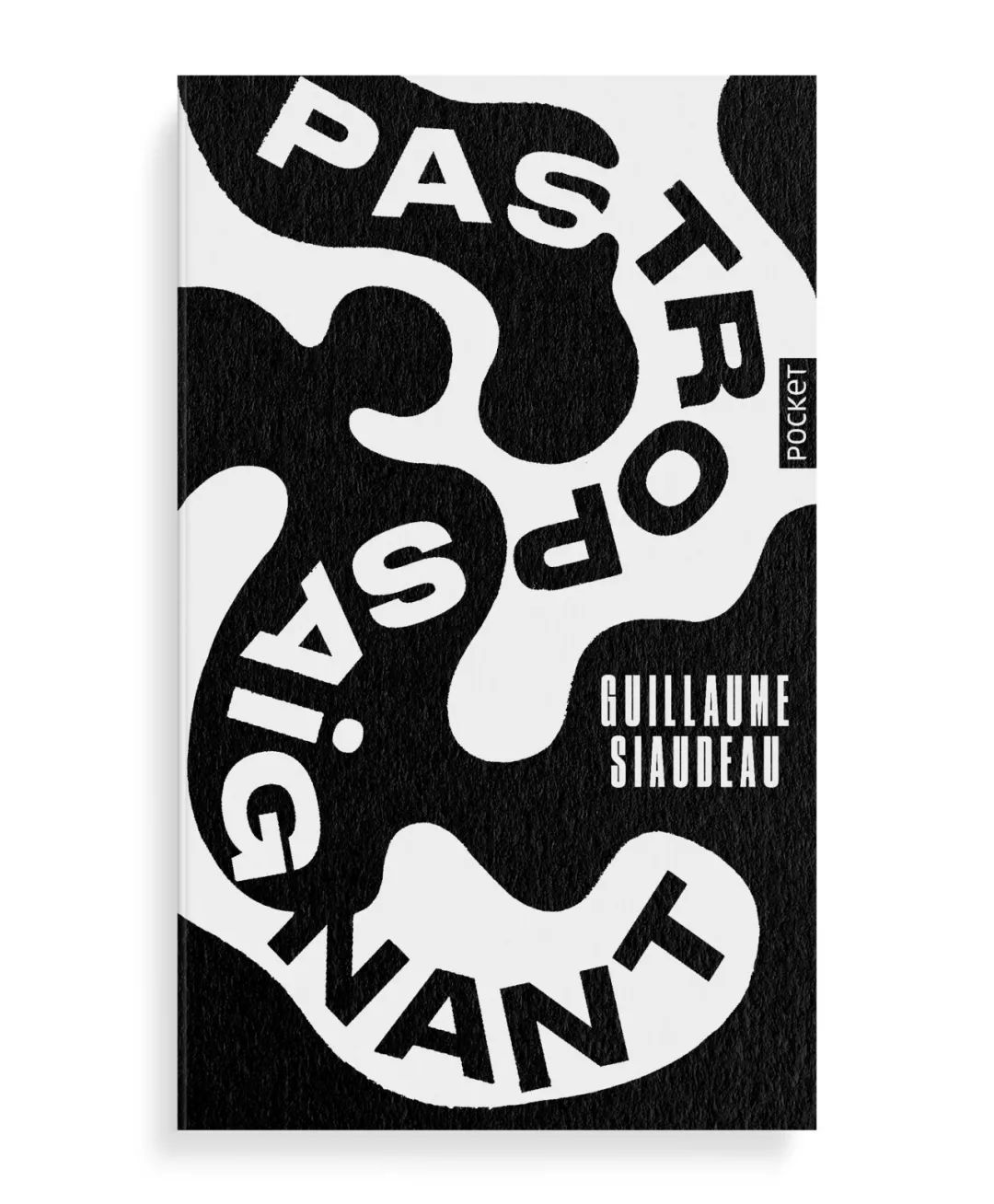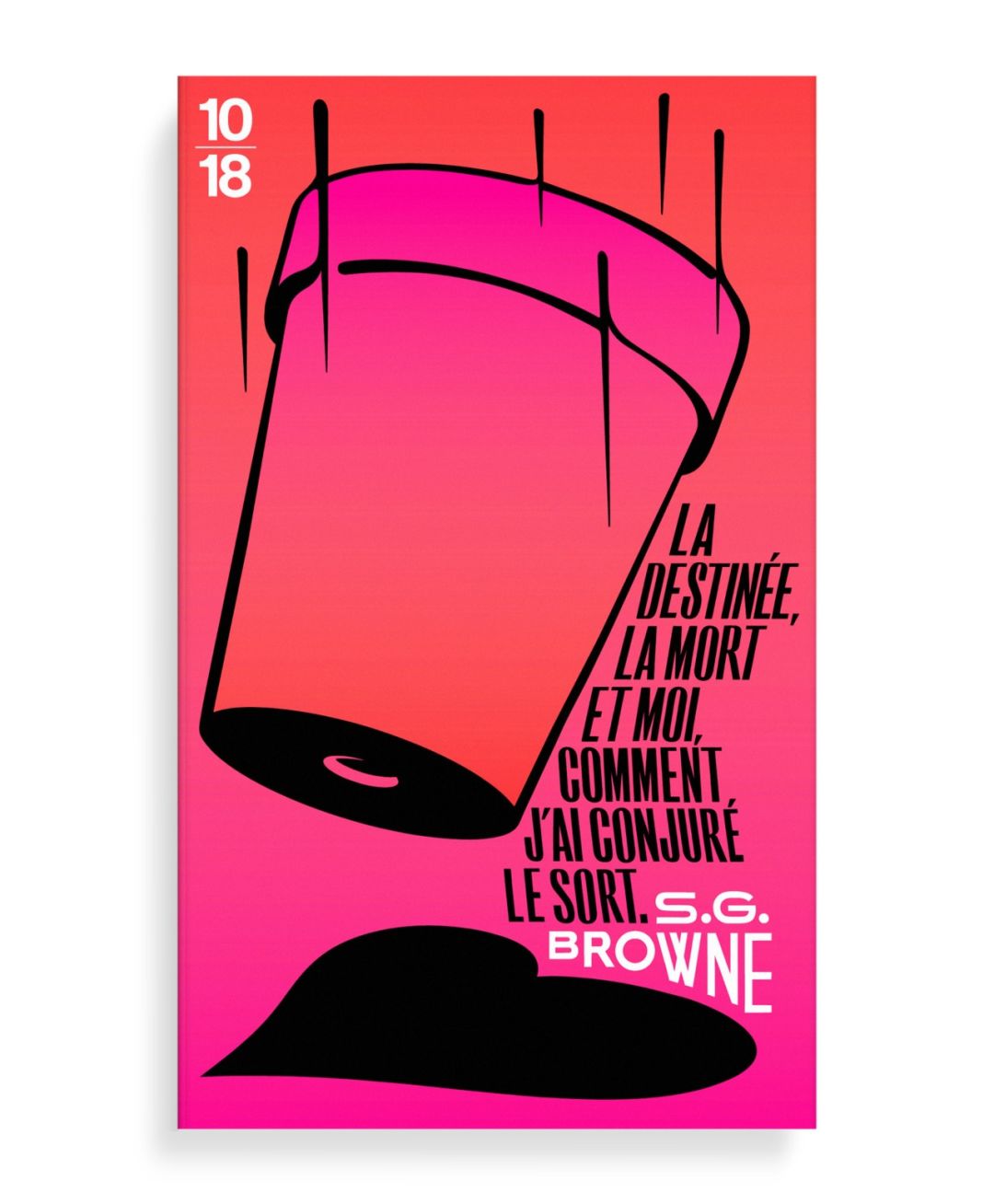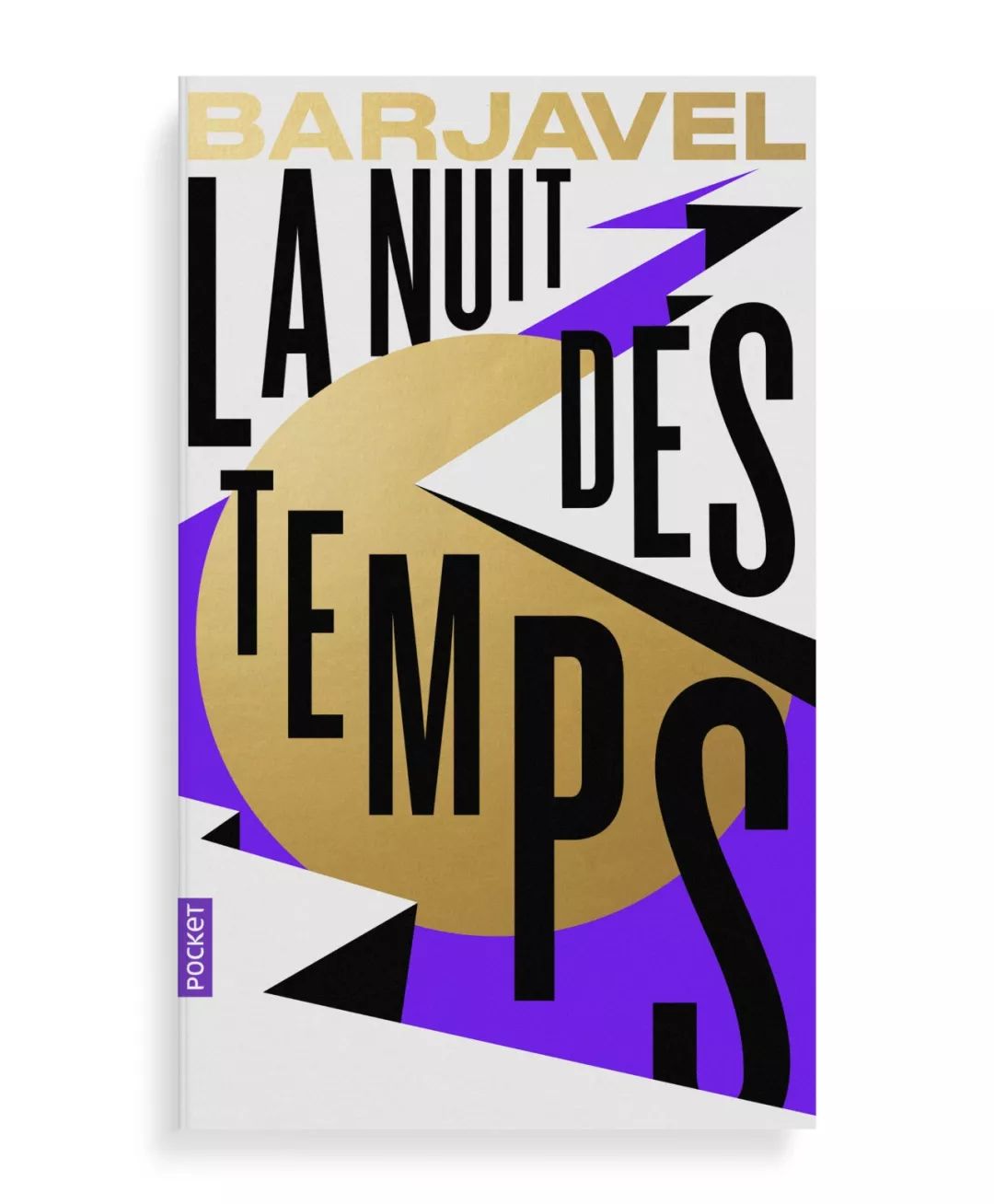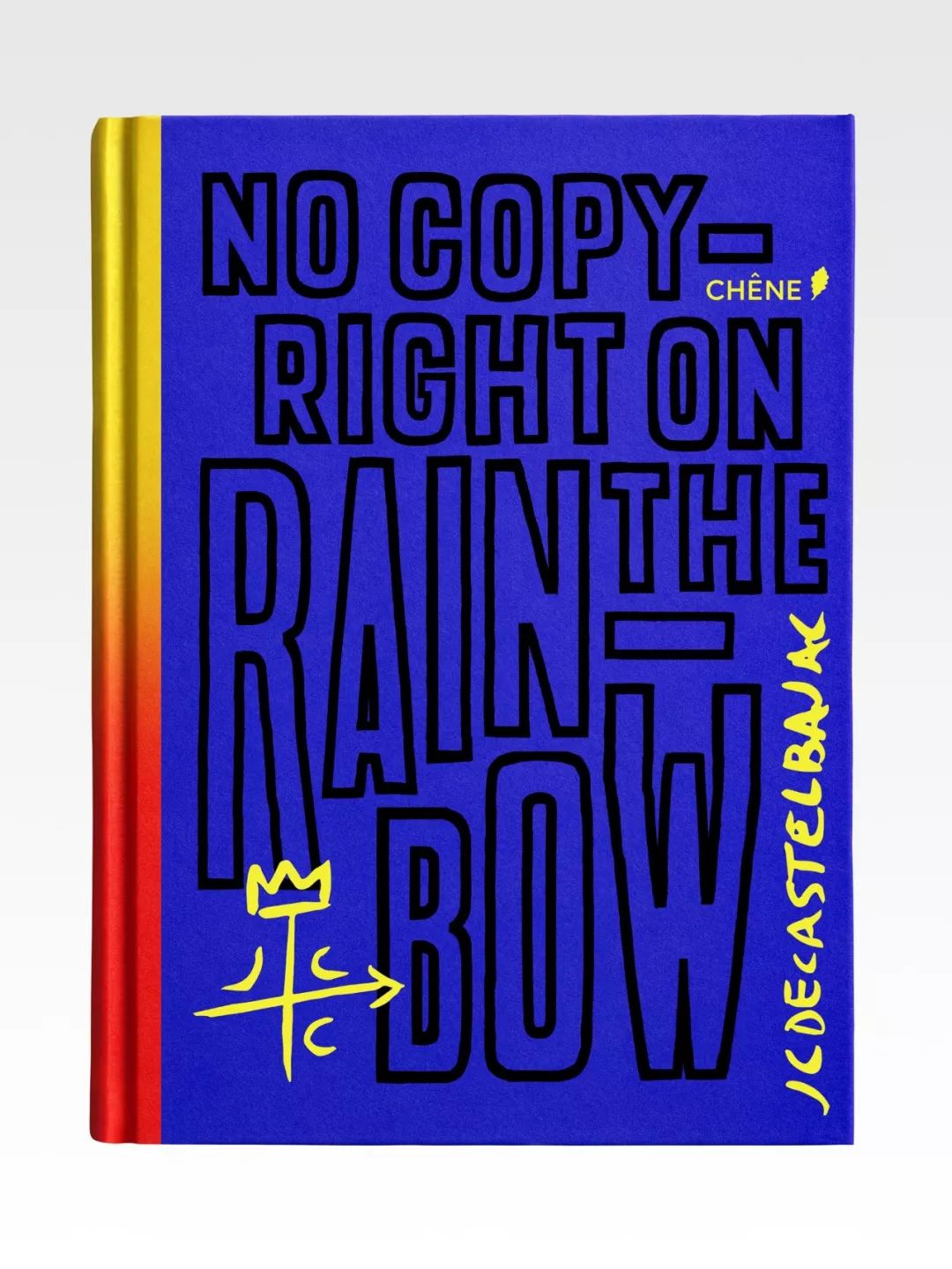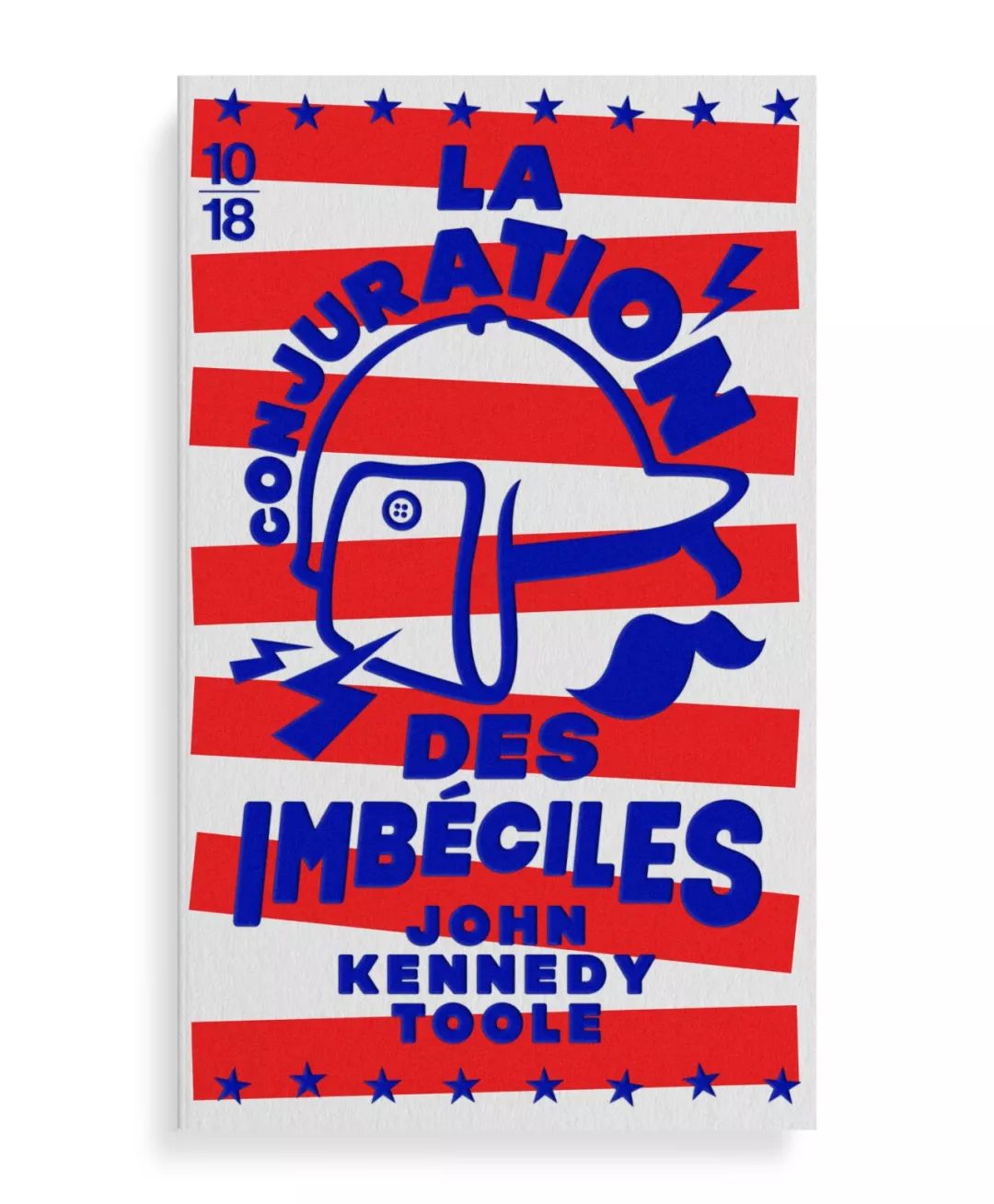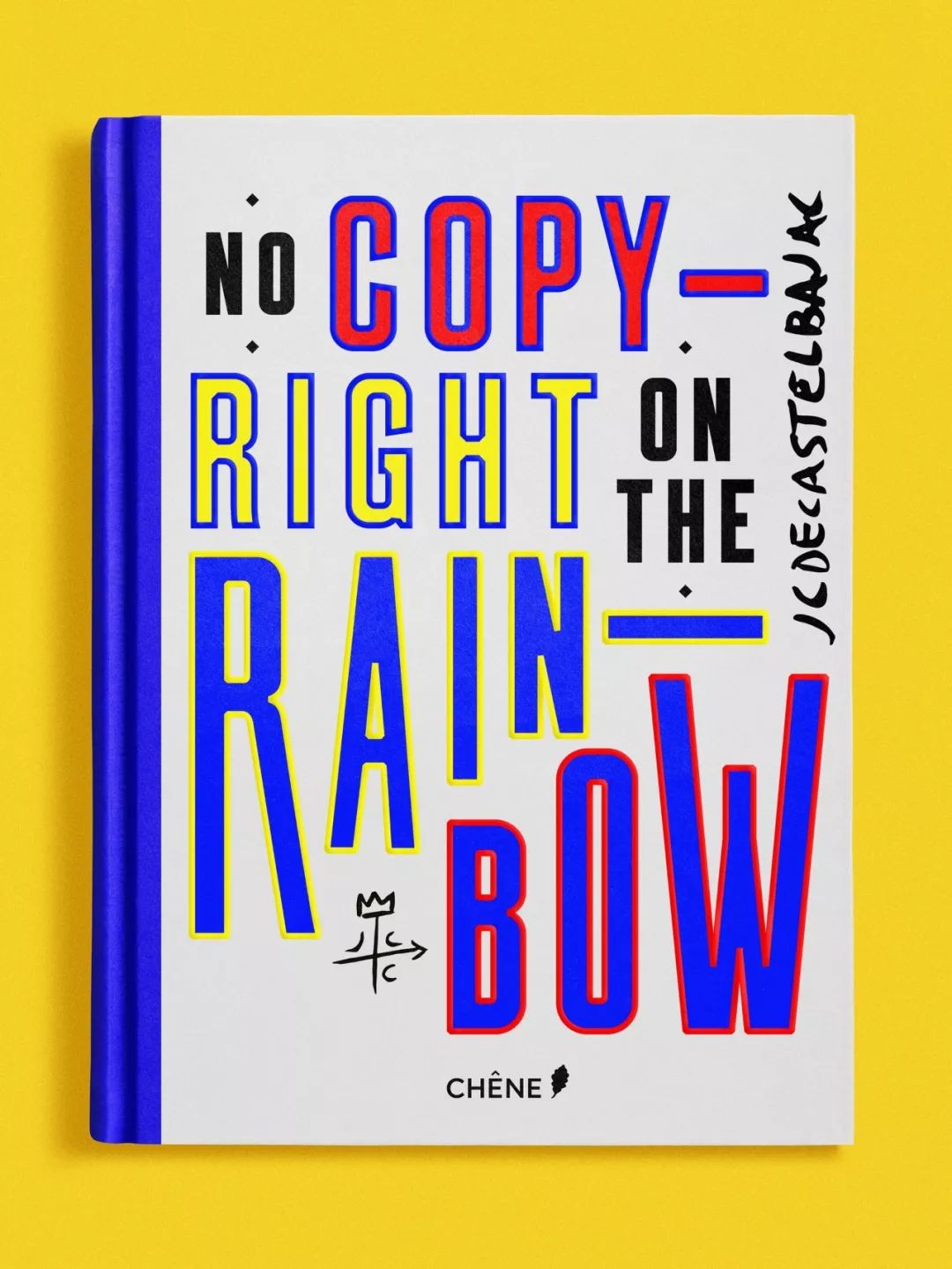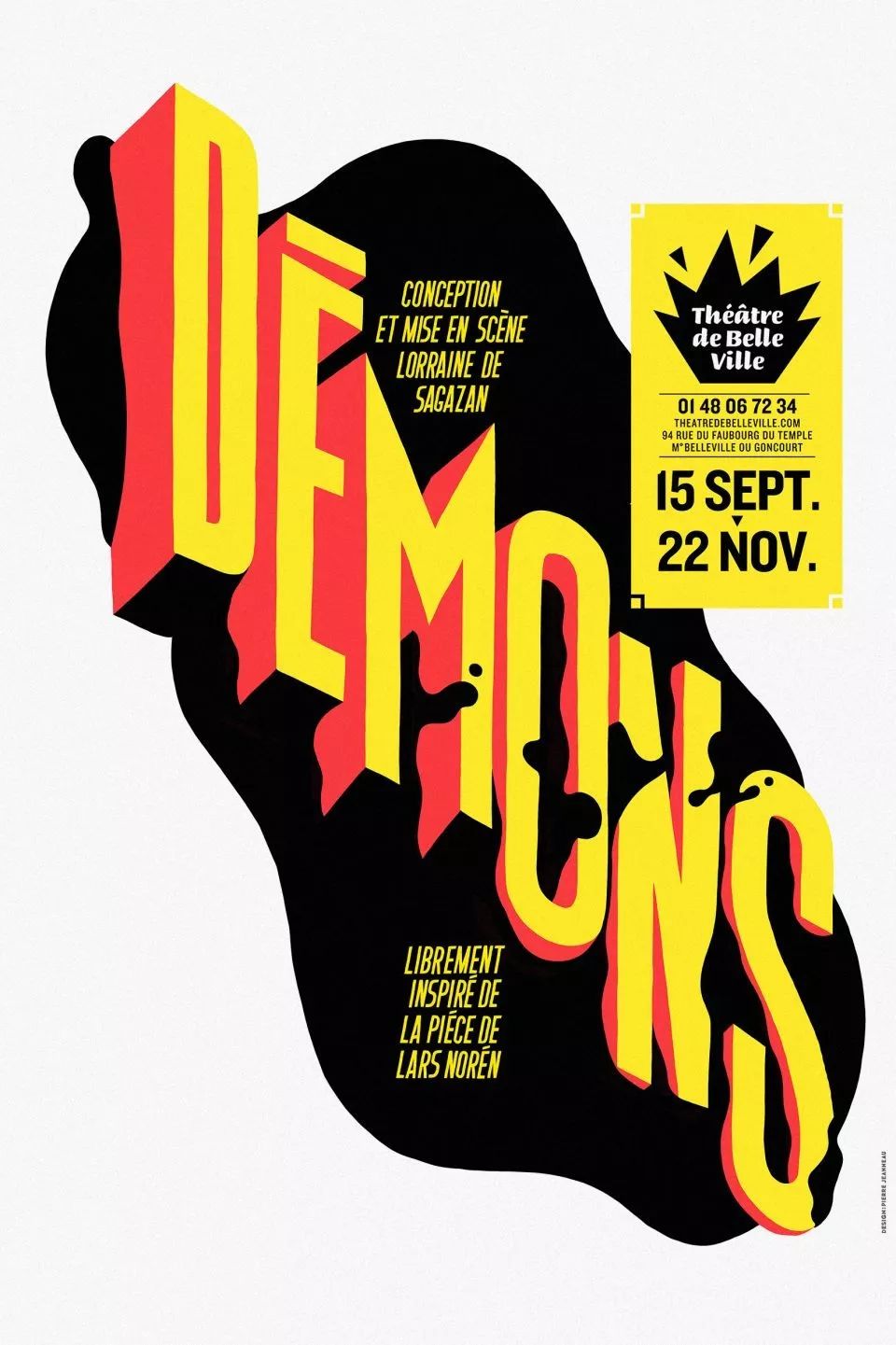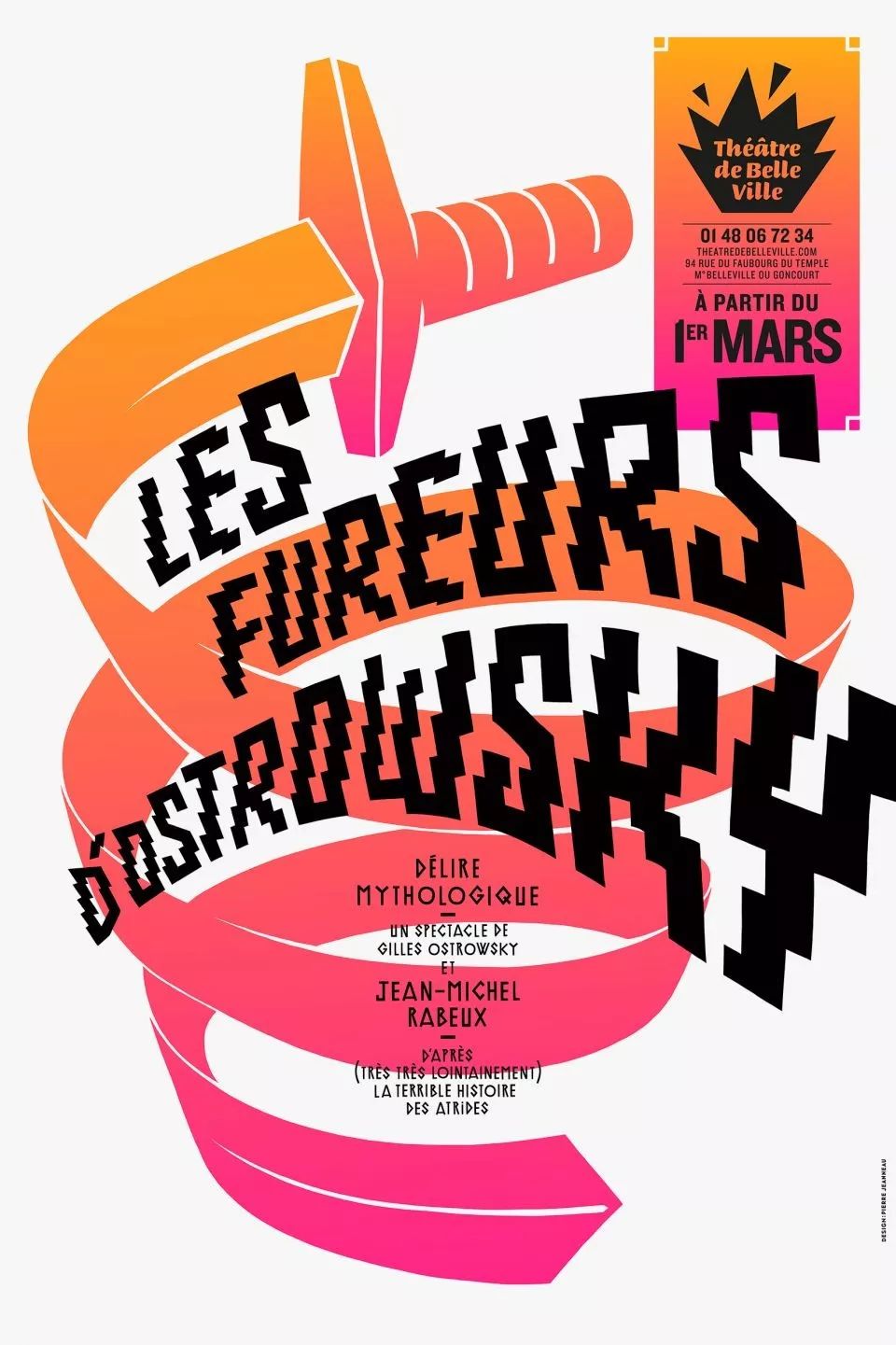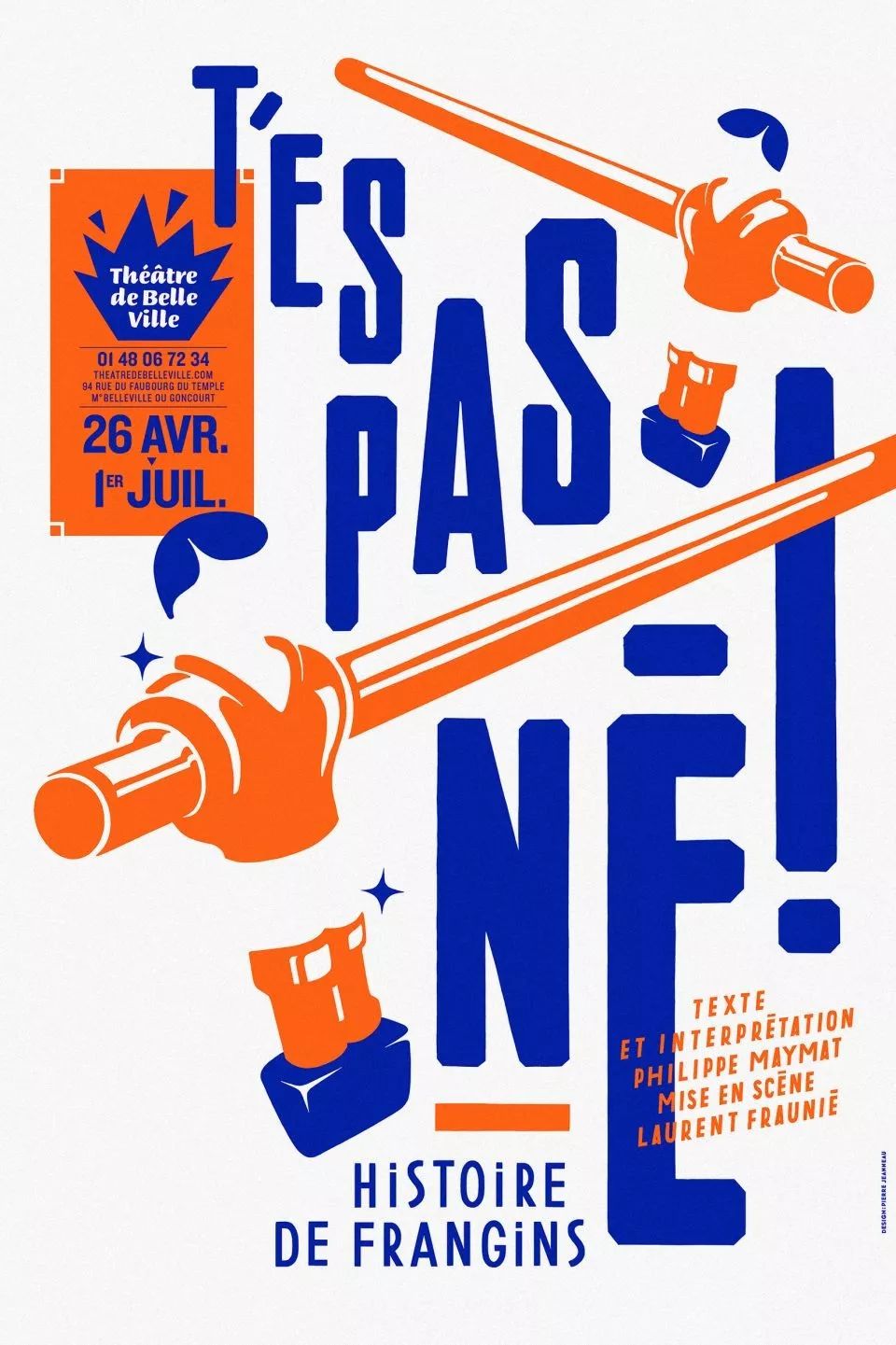
当文字以“形”舞蹈,简直太太太有趣了
Pierre Jeanneau 是一名法国的图形艺术家,所以在他的作品中,文字是拥有线条美的,就像小精灵在画面上跳舞,OMG!
书籍封面
剧院海报
贝尔维尔剧院
圣马丁门剧院
品牌视觉
为舞蹈公司创作的视觉效果
老佛爷百货公司
巴黎春天百货
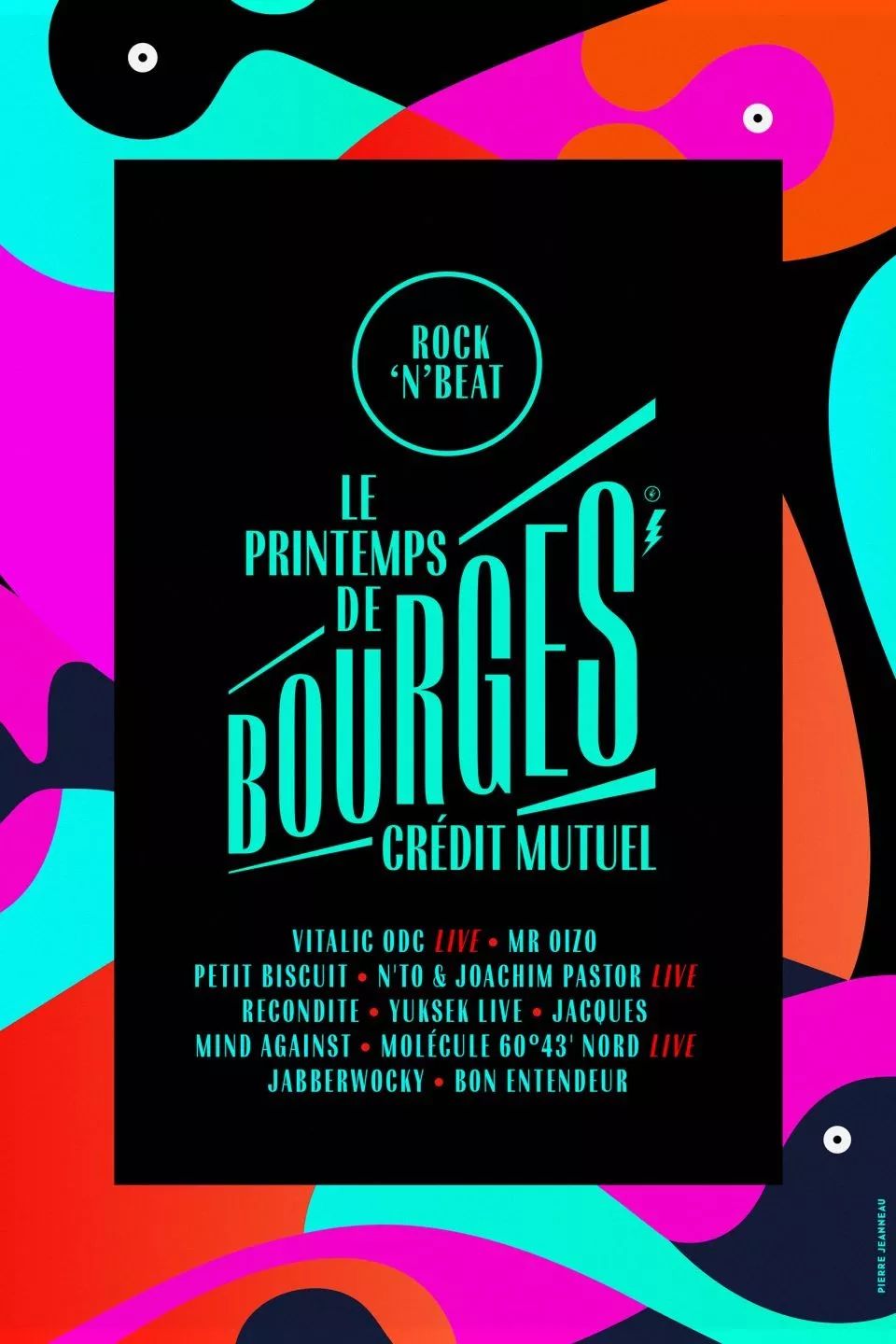
法国哥伦比亚年度视觉识别提案
品牌字体
巴黎耐克专卖店
为法国队新球衣发布而设计的字体
logotypes